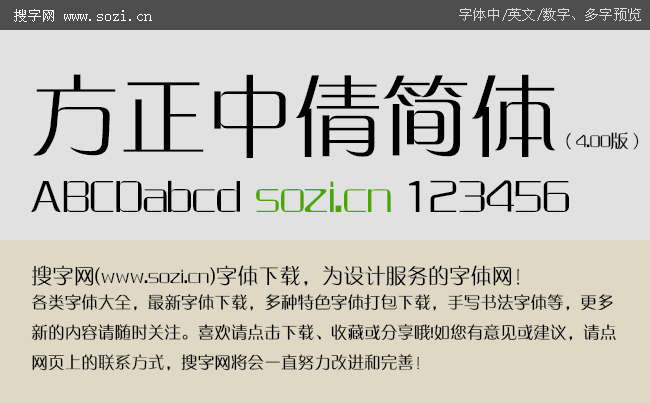
方正中倩簡(jiǎn)體4.0
搜字網(wǎng)給大家提供一款方正中倩簡(jiǎn)體下載。中倩體親切、幽雅、柔美和華麗,筆劃粗細(xì)對(duì)比適中,婉轉(zhuǎn)嫵媚,溫順乖巧,看似平淡無奇,卻能給人以美的感受。適用于個(gè)人用品、化裝品、食品、家居廣告宣傳使用環(huán)境。